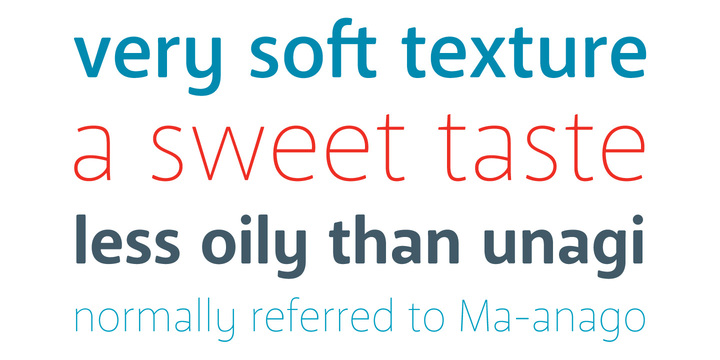
mal eine Nachfrage: Hast Du Dir die Anago damals gekauft? Und kannst Du Erfahrungswerte teilen?
mir ist gerade aufgefallen, dass in der myfonts-beschreibung steht:
Anago shares the same DNA as its sibling Macha, but is a completely different species than the former or any of my other sans serifs (Aaux Next, Air, Akagi Pro or Wasabi).
allerdings finde ich die akagi nahezu identisch und ging, auch des namens wegen, davon aus, dass das die eigentliche schwesterschrift der anago ist. schau dir am besten alle drei mal an, bevor du dich für eine entscheidest:
Stimmt. Spontan fällt einem natürlich gleich das unterschiedliche g ins Auge. Warum hat Neil Summerour wohl so viele fast identische Schriften unter unterschiedlichen Namen herausgegeben? Ich meine, klar, da gibt es schon eine schöne Auswahl an Alternativbuchstaben, aber vielleicht wäre es für den Kunden schlüssiger, wenn die Schriften alle zu einer Sippe gehörten und jeweils durch Zusätze wie »spornlos« zur Erklärung versehen wären.   :-?
Ich wollte die Schrift übrigens gar nicht unbedingt kaufen, ich bin bloß bei der Recherche drauf gestoßen und war neugierig, ob RoMi sie mal selber ausprobiert hat.
Von den Formen her gefällt mir – glaube ich – die Macha am besten.
hat was, finde ich – vorallem ein versal-ß, was aber eher so 'naja' ist.
Passt ja auch ein wenig in diese von Dir gesuchte Kategorie, oder?:
Zumindest musste ich daran denken, als ich sie das erste Mal sah …
ja, darum war sie mir damals aufgefallen, hatte sie aber nicht gekauft.
ich schau sie mir jetzt nochmal paar minuten an, wenn sie mich noch anmacht dann schlag ich evtl. doch noch zu :)
ich habe mir die drei schriften noch mal genauer angeschaut. meines erachtens ist das ein fall wie die adria grotesk, bei der man die formen, die sich zwischen aufrechter und kursive unterscheiden, bequem in einen stilistischen satz hätte packen können. das lateinische grundalphabet der macha ist, bis auf einige zeichen (a, b, d, g, J, j, K, k, l, M, p, Q, q), exakt identisch mit der akagi. und das was sich unterscheidet, sind kleinigkeiten. das ganze gelaber bei myfonts (»completely different species«) hat inhaltlich keinerlei hand und fuß. es wäre ehrlicher, die macha als ›akagi humanist‹ (oder so) zu vermarkten bzw. die paar zeichen eben in einen stilistischen satz zu packen. die anago wiederum ist nichts anderes als eine akagi rounded. das einzig neue daran ist das schreibschrift-›y‹. alle anderen lateinischen basisbuchstaben unterscheiden sich nicht oder in bloß kosmetischen details. die akagi, veröffentlicht 2007 (bzw. 2011 als pro-version), ist also die originäre gestaltung, von der die anago und die macha (2012) abgeleitet wurden. interessanterweise kostet die akagi auch 425 dollar, während die anago und die macha bloß mit 60 bzw. 50 euro zu buche schlagen (und das ist auch dann noch ein großer unterschied, wenn man rausrechnet, dass die akagi eine menge strichstärken mehr hat als die beiden anderen). diese zusammenhänge als schriftanbieter so undeutlich bzw. irreführend darzustellen, finde ich doch ein bisschen …
Vor allem verstehe ich den Sinn dahinter nicht …  :-? Mal von der mangelnden Praktikabilität abgesehen – wer kauft denn die teure Variante, wenn er für kleines Geld die beiden anderen Varianten kaufen kann? Schneidet sich der Gestalter bei der Strategie nicht ins eigenen Fleisch?
Mein persönlicher Eindruck zu Positype ist, dass oft mit viel Ehrgeiz und guten Ideen an Projekte rangegangen wird – siehe Air mit zwei Kursiven (echt und oblique mit anderem Winkel) – aber irgendwie oft bei genauerem Hinsehen doch immer wieder der letzte Schliff fehlt oder Potential einfach verschenkt wurde. Zum Beispiel Romp (je 3 Alternativen pro Buchstabe, aber unterschiedliche komlexe/einfache a- und g-Formen). Clear Sans, eine angeblich humanistische Geometrische mit weichen Formen, die aber letztendlich nur beim a zu finden sind. Oder eben die extrem gut ausgebaute Air (81 Schnitte!) deren Schriftbild aber leider nicht so harmonisch und sauber erscheint, dass sie für mich als Arbeitstier trotz anfänglicher Begeisterung ernsthaft in Frage käme. Schade.
hab mir die anago nochmal angesehen – abgesehen von den dingen die thierry aufgezählt hat, gefällt sie mir schon.
letztendlich ist sie mir aber von der formsprache im vergleich zur leitura dann doch zu ähnlich.
bei flüchtiger betrachtung fällt das softe/abgerundete nicht sehr auf, darum denke ich fahre ich mit der leitura erstmal ganz gut.
das ist auch mein eindruck, r::bert. ich finde die qualität der schriften okay, aber nicht überragend. die buchstaben sind annehmbar gezeichnet, aber im detail ist die umsetzung teilweise lieblos. ich hatte vor jahren mal ein auge auf die aaux und die epic geworfen:
beide fand ich dann doch nicht mehr so harmonisch und gelungen, als ich etwas näher hinsah, und in beiden fällen habe ich mich letztlich gegen einen kauf entschieden. bei der akagi und all ihren ableitungen geht es mir ähnlich: auf den ersten blick nicht schlecht, im detail dann aber doch nicht so toll. das ist in der tat schade.
Vor allem verstehe ich den Sinn dahinter nicht …  :-? Mal von der mangelnden Praktikabilität abgesehen – wer kauft denn die teure Variante, wenn er für kleines Geld die beiden anderen Varianten kaufen kann? Schneidet sich der Gestalter bei der Strategie nicht ins eigenen Fleisch?
nun ...
1. hat der designer somit einen größeren output, wenn täglich neue schriften bei myfonts erscheinen, ist diese entscheidung sicher nicht ganz unwichtig.
2. vielleicht verkauft sich die teure variante ja nicht und man versucht so etwas 'werbung' für diese zu machen, bzw. den markt aufzurollen und zerhakt das große akagi-paket in kleine.
preislich eher oben angesiedelt, aber evtl. eine alternative zur Leitura und Akagi ist Vinkel
Tolle Schrift. Die werde ich mal im Auge behalten. Die Tanger Serif von ihnen ist auch sehr erfrischend und erstaunlich umfangreich ausgebaut (könnte man vielleicht sogar als Kombischrift in Betracht ziehen – naja nicht ganz):
Aber wirkt das g auch etwas »wackelköpfig« auf Euch?